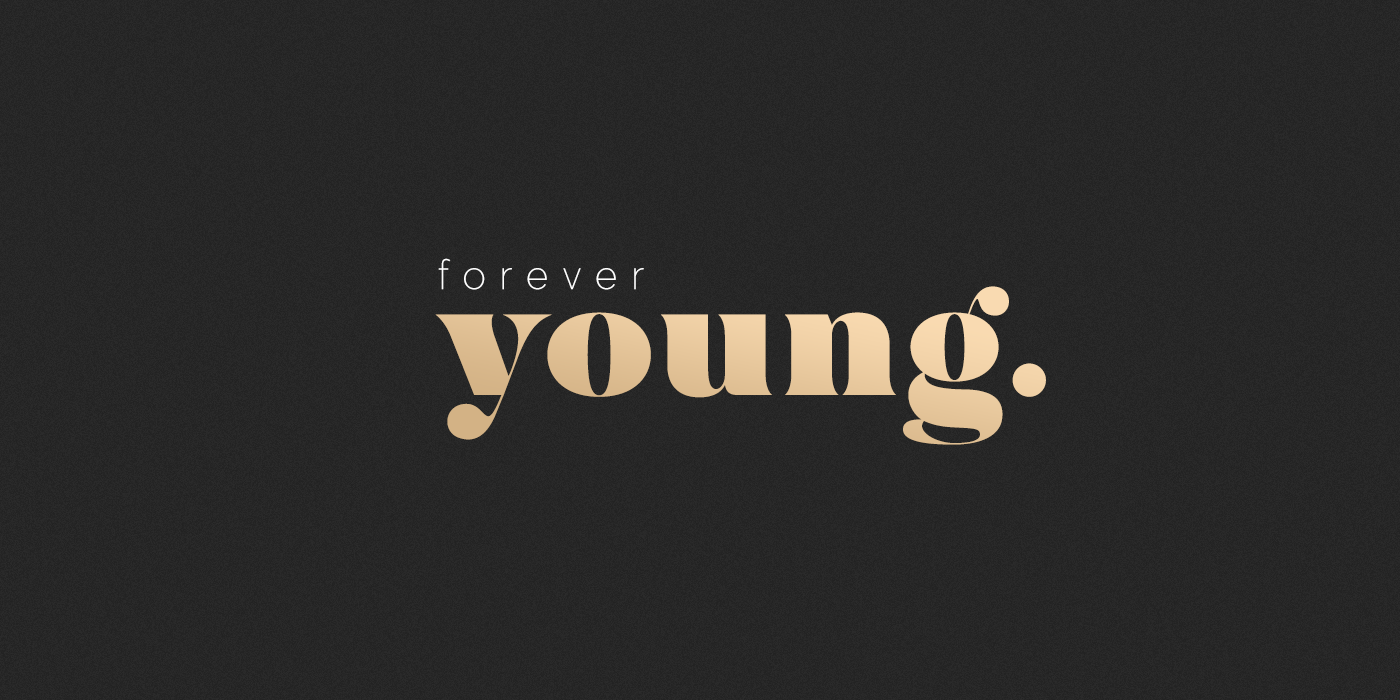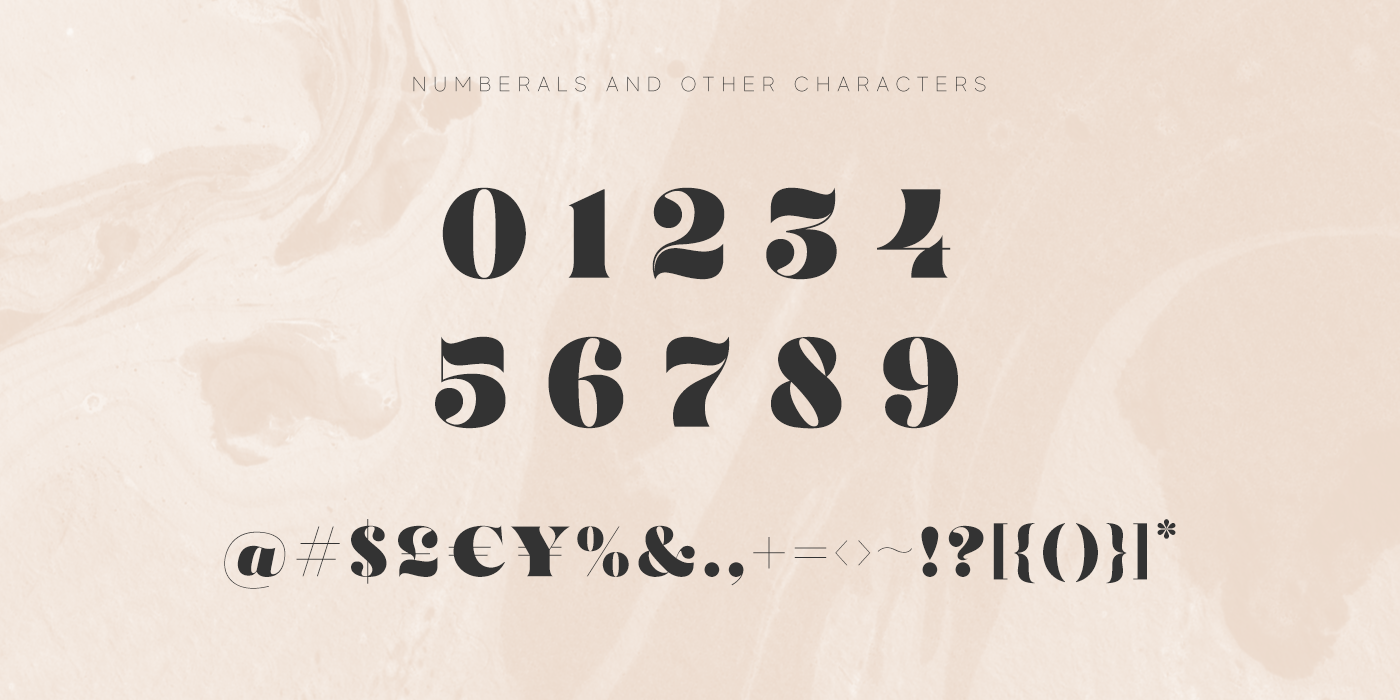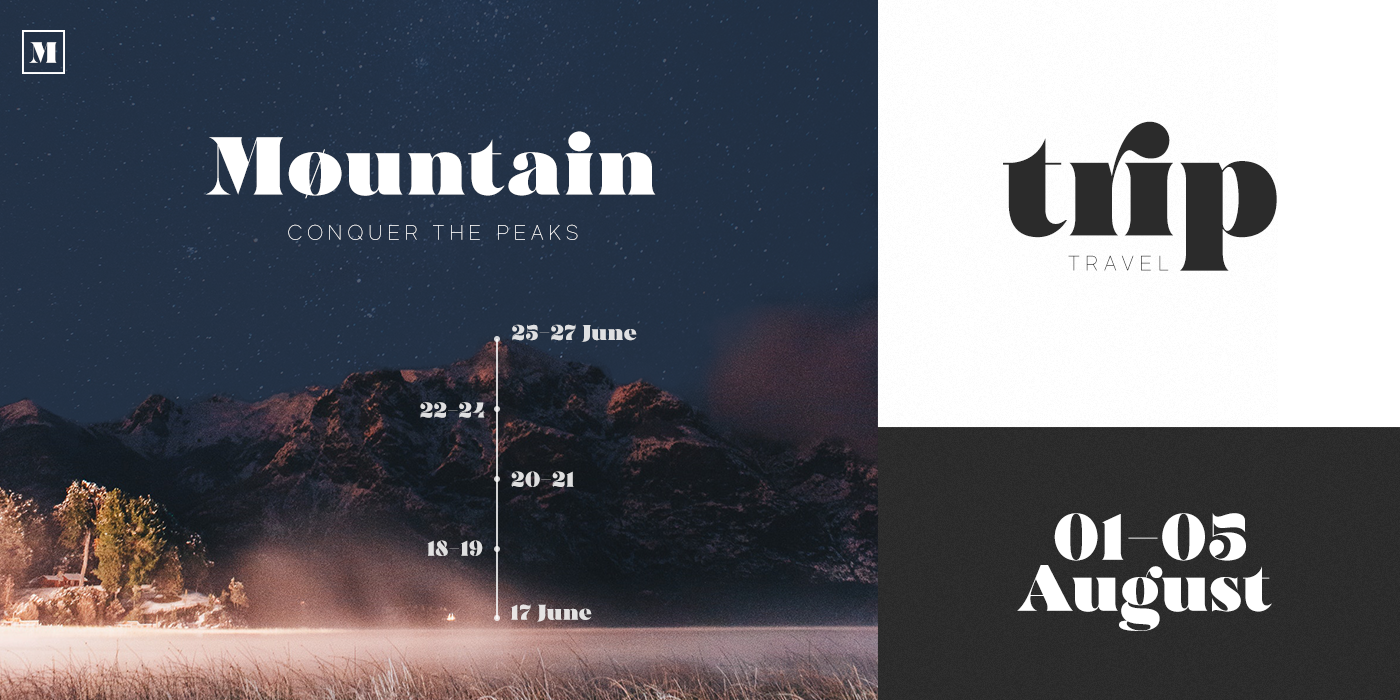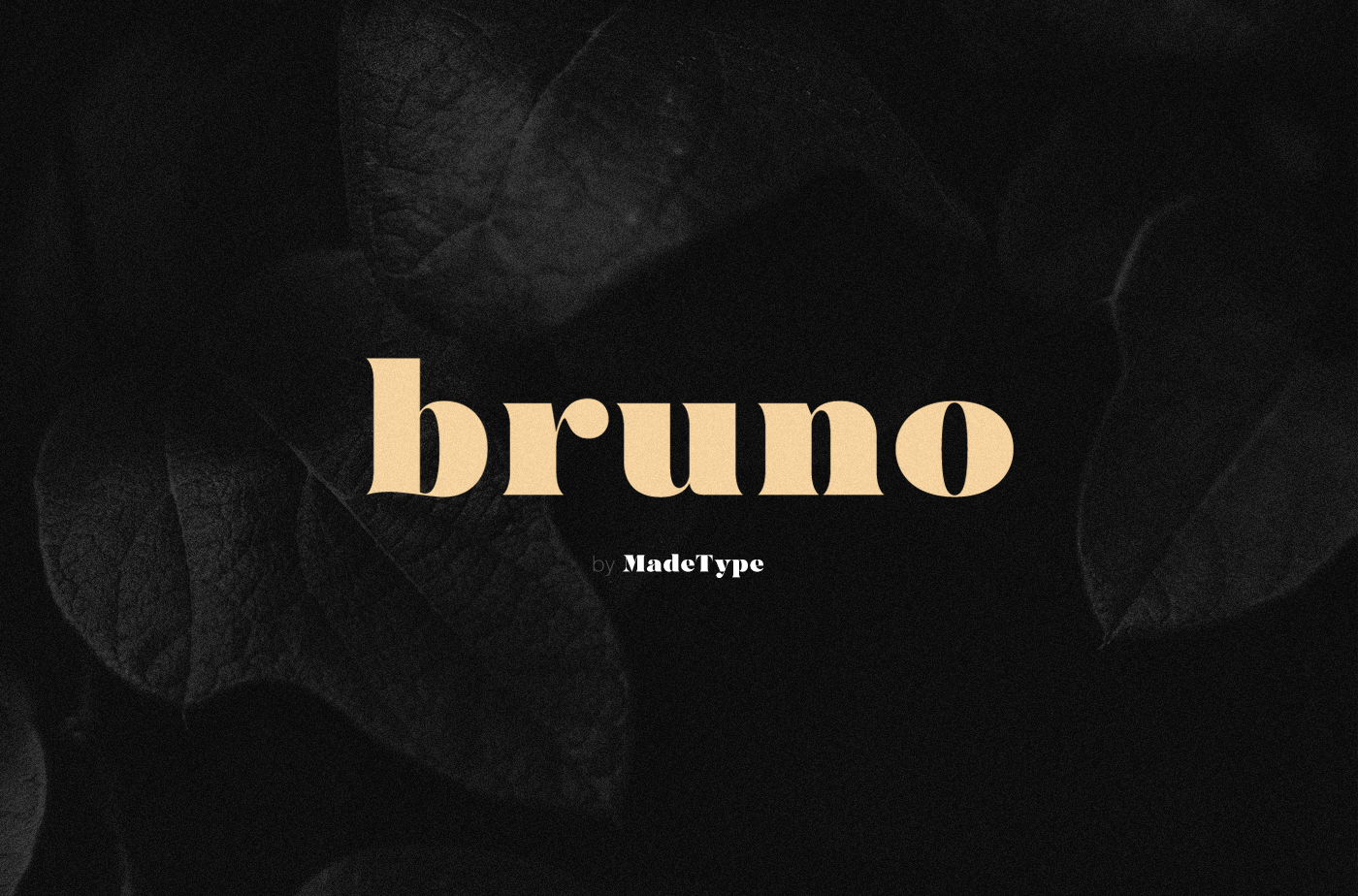
Font del giorno: MADE Bruno
Il font che vi presentiamo oggi é: MADE Bruno
SOUTHAMPTON è il nuovo font realizzato da  MadeType
Forme semplici e strutture ornamentali ridotti, MADE Bruno è particolarmente adatto per i titoli, ma può anche essere utilizzato per scopi  editoriali grazie alla sua vasta serie di lettere e caratteri  alternativi ivi compresi i numeri, perfetto per qualsiasi progetto di design come loghi e branding, inviti di cerimonia, post sui social, pubblicità, packaging, design di prodotti quando la necessità e far uscire il nome prima di tutto.